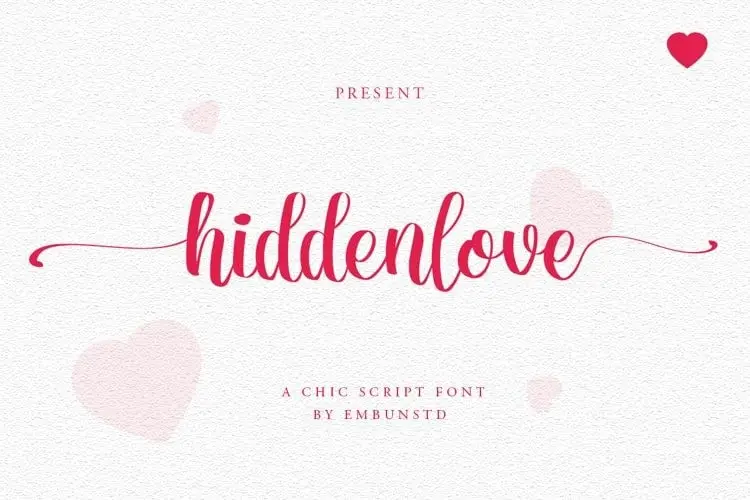
Hiddenlove Calligraphy Font – Download Grátis
A Hiddenlove Calligraphy Font é uma fonte que encanta a quem a vê. Seu charme delicado emerge do seu traçado meticuloso, desenhado com mão e compartilhado pela rezkistore. Este tipo de graffiti apresenta linhas suaves, contornos vívidos e alternativas impressionantes, mantendo seus influentes elementos de calligrafia ao mesmo tempo modernos e inovadores. A Hiddenlove Calligraphy Font é a escolha perfeita para quem busca uma fonte elegante que também carrega um toque de frescura. Seja para anúncios gráficos ou projetos de design editorial, ela trará o seu toque único à sua arte digital.